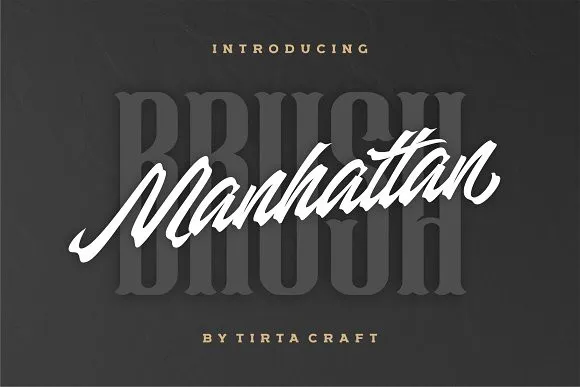
Manhattan Brush Ink Script Font – Fonte Grátis
Manhattan Brush Ink Script Font
Aqui está uma descrição em português para a página de download da fonte ‘Manhattan Brush Ink Script Font’, seguindo as orientações: Bem-vindo à Manhattan Font, um belo e elegante conjunto de letras cursivas feito à mão com traços de caneta e textura. Criado cuidadosamente por Typovecto Std., esta fonte é perfeitamente adaptada para qualquer projeto criativo. A Tirta Craft introduziu a primeira tipografia comercial da sua linha, apresentando uma fonte que traz o charme dos anos 50 ao seu design atual. Manhattan Brush Ink Script Font oferece um toque de luxo e elegância sem perder a modernidade, tornando-se um recurso inovador para quem busca dar vida aos seus projetos digitais com sofisticação. Com sua textura suave e linhas clássicas, esta fonte é ideal tanto para uso em materiais impressos quanto online. Suas características elegantes e limpas permitem que você personalize seu layout de acordo com suas necessidades, criando um texto profissional e atraente. Se estiver procurando por uma fonte que combina charme antigo com modernidade contemporânea, Manhattan Brush Ink Script Font é uma ótima escolha. Seu formato comercial permite que você use este recurso para seus projetos sem restrições legais. Descubra como essa fonte pode revolucionar a aparência de seus trabalhos digitais e adquira sua cópia agora para aproveitar todas as suas potenciais possibilidades!